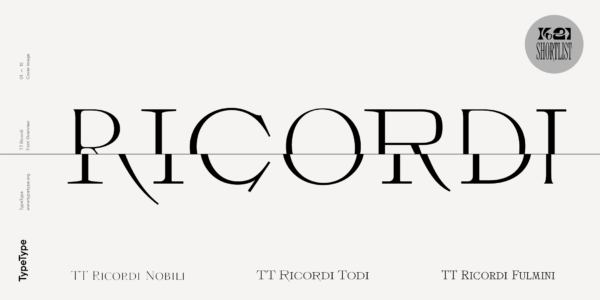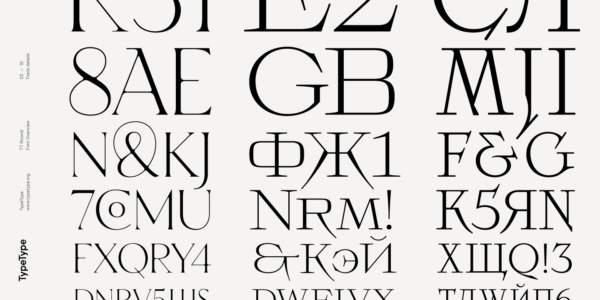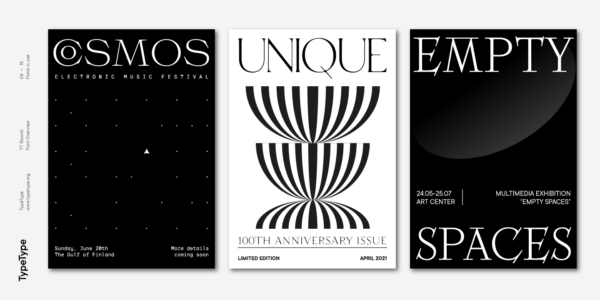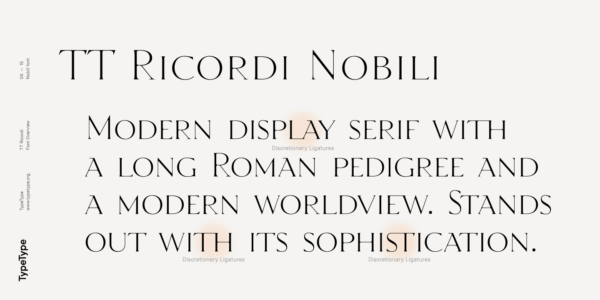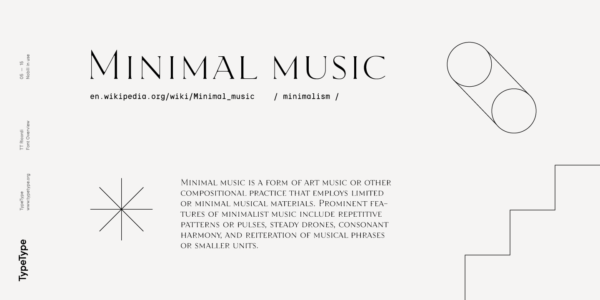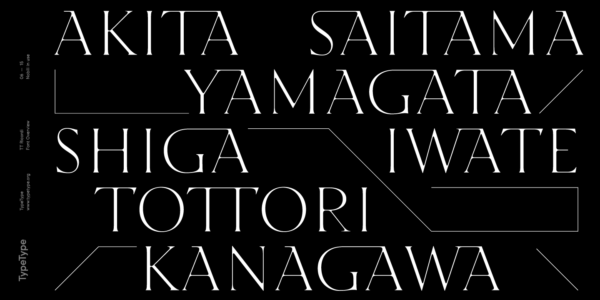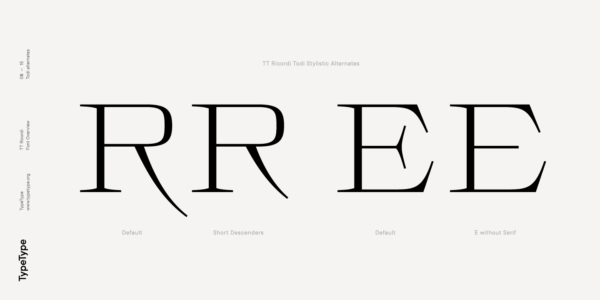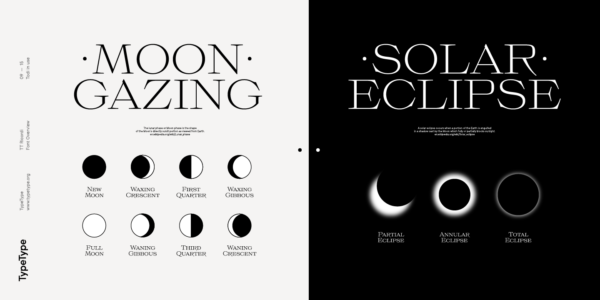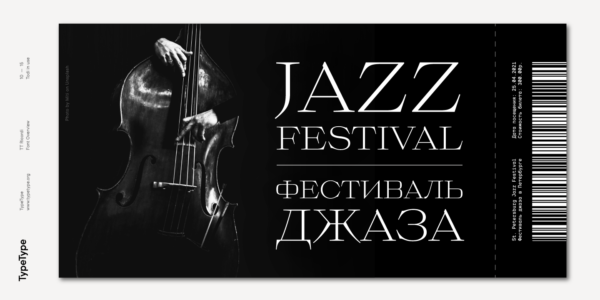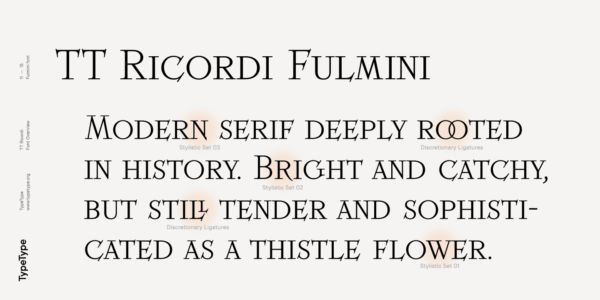
TT Ricordi
TT Ricordi — ТТ Рикорди
Произносится «ТТ Рикорди». «Ricordi» — производное слово от ricordo, в переводе с итальянского «воспоминание». Буквы «TT» являются аббревиатурой названия компании
TT Ricordi — коллекция из трёх дисплейных заголовочных антикв, у каждой из которых своя история. Эта гарнитура поможет решить ряд дизайнерских задач.
TT Ricordi
The TT Ricordi font family is a collection of three display heading serifs designed to significantly diversify the traditional font palette. Each font from the TT Ricordi family was drawn by a separate designer and has its own story.
TT Ricordi
The fonts from the TT Ricordi typeface turned out to be quite display and contemporary, but at the same time, they retained subtle references to historic inscriptions. The fonts fit perfectly both on the covers of book classics and in glossy magazine layouts.
Гарнитура TT Ricordi является коллекция из трёх дисплейных заголовочных антикв, призванных значительно разнообразить традиционную шрифтовую палитру. Каждый шрифт из гарнитуры TT Ricordi рисовался отдельным дизайнером и за каждым шрифтом лежит своя история. При этом все три шрифта близки по толщине и схожи своими кассовыми составами, и представлены в прописном и капительном наборе, который заменяет собой строчные знаки. В шрифтах есть широкая поддержка Латинских языков и поддержка базовой кириллицы.
Своё начало проект берёт из до-короновирусных туристических путешествий по Италии, в рамках которых у нашего артдиректора Юлии накопилось много фотографий исторических надписей и табличек. Многие из этих надписей имели интересный характер или необычные формы знаков. Нам захотелось с ними поработать, попробовать их переосмыслить, и по возможности сделать их ультрасовременными и доступными для современного шрифтового пользователя.
Шрифты из гарнитуры TT Ricordi получились довольно акцидентым и современным, но при этом они сохранили небольшие отсылки к историческим надписям. Шрифты прекрасно ложатся как на обложки книжной классики, так и в глянцевые макеты. Их также можно использовать в плакатах и в упаковке или же можно сделать их основным выразительным элементом брендинга компании. Кроме того, все три антиквы из гарнитуры TT Ricordi отлично сочетаются с функциональными гротесками, например с TT Norms Pro или c TT Commons.
TT Ricordi Todi — это шрифт с широкими засечками с классической основой и современным характером. Шрифт получился изысканным, но резким, местами даже напористым и агрессивным. Шрифт нарисовала Юлия Гонина, а в основу проекта легли таблички с выгравированными названиями улиц небольшого итальянского городка Тоди. Главной задачей было расшифровать характерные черты знаков и подчеркнуть их на современный лад. Кроме того, нужно было нарисовать кириллицу, которая по своей выразительности не уступала бы латинице.
У TT Ricordi Todi довольно широкие пропорции, и контраста в них практически нет. Главной особенностью шрифта является сочетание плавных округлых форм с нарочито квадратными формами. Кроме того, шрифт характеризуется острыми и четкими деталями символов, гипертрофированными надстрочными и подстрочными элементами и приглушенным контрастом. Среди интересных особенностей шрифта вы можете выбирать между характерными длинными выносными и верхними элементами и их более умеренными версиями, вы можете найти стилистический набор с треугольными точками, альтернативные версии символов EF и две формы буквы Ф, круглую и квадратную. В шрифте TT Ricordi Todi 876 глифов, и целый набор полезных фич, таких как: aalt, ccmp, locl, numr, ordn, tnum, pnum, case, dlig, salt, ss01, ss02, ss03, ss04, сс05, сс06, сс07, сс08, сс09, сс10, calt.
TT Ricordi Fulmini является модной современной антиквой, крепко держащаяся за исторические корни. Шрифт получился похожим на цветок чертополоха: яркий и цепляющий, но всё ещё утончённый и нежный. TT Ricordi Fulmini нарисован Мариной, а первоначальным вдохновением для проекта послужила надпись на алтаре из национальной галереи Умбрии в Перуджи. В процессе вытягивания «в современность» шрифт полностью преобразился и раскрылся с новой стороны.
Главной цепляющей деталью в шрифте TT Ricordi Fulmini являются агрессивные и достаточно острые диагональные засечки. Кроме того, в процессе работы над шрифтом появилось несколько графических решений, например монозасечки и очень каллиграфичные с духом историзма соединения диагональных штрихов. Нам захотелось сохранить их, и таким образом в шрифте появились 4 тематических визуальных сета, благодаря которым можно сильно поменять восприятие шрифта. Кроме того, в шрифте есть набор интересных дискретных лигатур.Всего в шрифте TT Ricordi Fulmini 793 глифов, и целый набор полезных фич, таких как: aalt, ccmp, locl, numr, ordn, tnum, pnum, case, dlig, ss01, ss02, ss03, ss04, ss05, ss06, ss07, ss08, ss09, ss10, calt.
TT Ricordi Nobili — шрифт с засечками, имеющий богатую римскую родословную и современный взгляд на мир. Он выделяется из толпы своей утонченностью и элегантностью. Шрифт был нарисован Анной Тихоновой и вдохновлен надписью, высеченной на каменном полу собора во Флоренции. Из-за того, что люди ходили по надписи, некоторые буквы со временем истончились и стерлись. Именно это ощущение исчезающих или мерцающих элементов мы хотели запечатлеть и реализовать в проекте.